font-family: 'Kanit', sans-serif;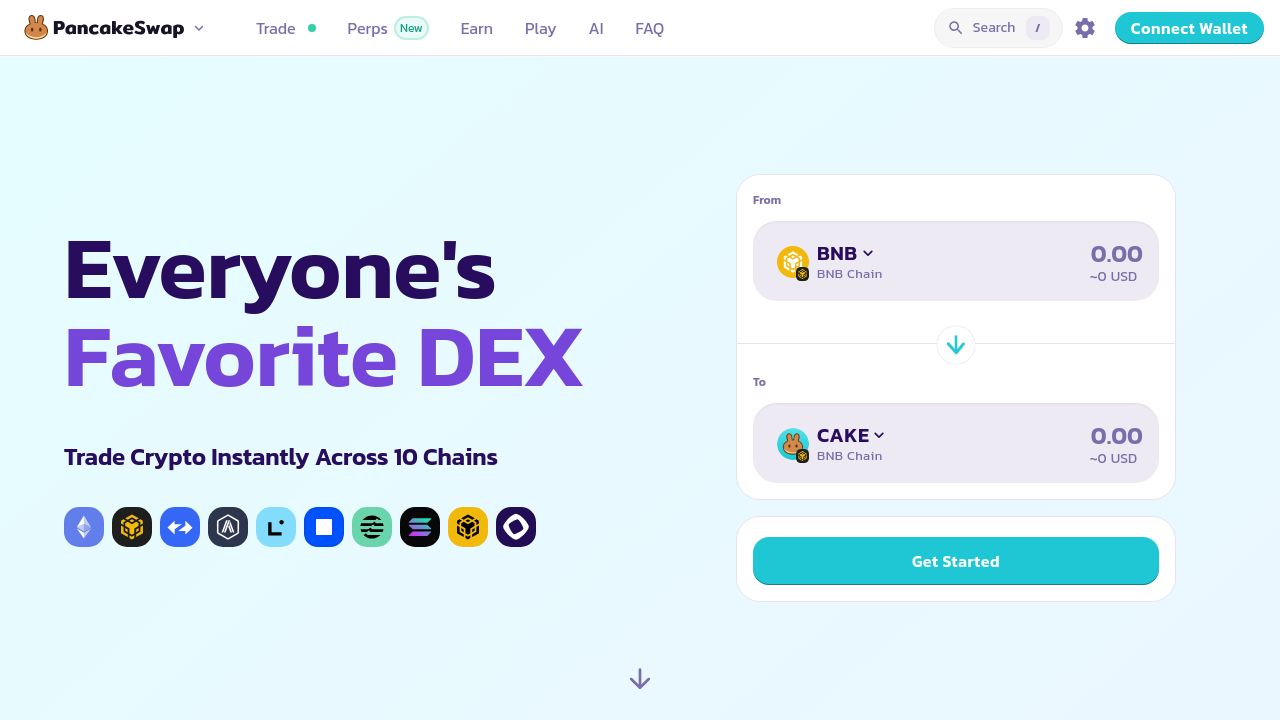
Pancakeswapはどのフォントを使っている?
Pancakeswap.financeはメインフォントとしてKanitを使用しています。 Arial, Roboto, helvetica-neueとSegoe UIはフォールバックとして指定されています。 10種のフォントを検出、最終確認: 2026年6月1日。
PancakeSwapは、暗号通貨の取引や獲得を行うためのオールインワンのマルチチェーンDEXです。このサイトでは、Kanitフォントを使用しており、その多様なウェイト(400、500、600、700、800)は、視覚的な柔軟性とインパクトを提供しています。また、swiper-iconsフォントが追加され、アイコン表現を強化しています。これにより、ユーザーにとって直感的で魅力的な体験が実現されています。
Pancakeswap.financeはどのフォントを使っている?
Pancakeswap.financeはメインフォントとしてKanitを使用しています。 Arial, Roboto, helvetica-neueとSegoe UIはフォールバックとして指定されています。 10種のフォントを検出、最終確認: 2026年6月1日。
pancakeswap.financeで使用されているフォントは何ですか?
pancakeswap.financeでは、主にKanitフォントとswiper-iconsフォントが使用されています。Kanitは多様なウェイトがあり、視覚的な表現力が豊かです。
Kanitフォントは他のフォントと比べてどうですか?
Kanitフォントは、特にデジタル環境において読みやすさとスタイルのバランスが優れています。RobotoやArialと比べると、個性的で親しみやすい印象を与えます。
swiper-iconsフォントのスタイルやウェイトは?
swiper-iconsフォントは、ウェイト400のカスタムアイコンフォントです。多様なアイコンを提供し、視覚的な情報を効果的に伝えるために設計されています。